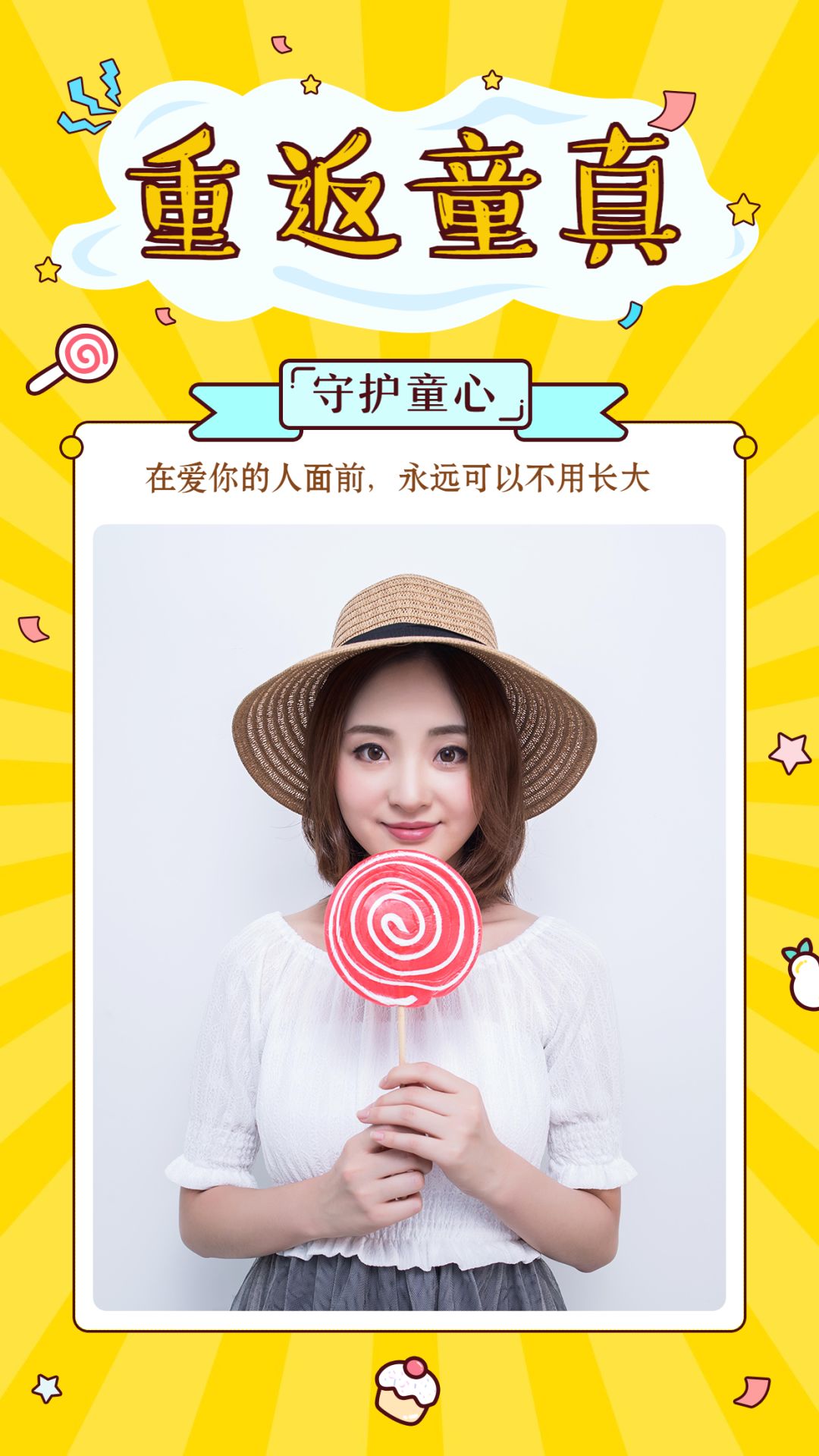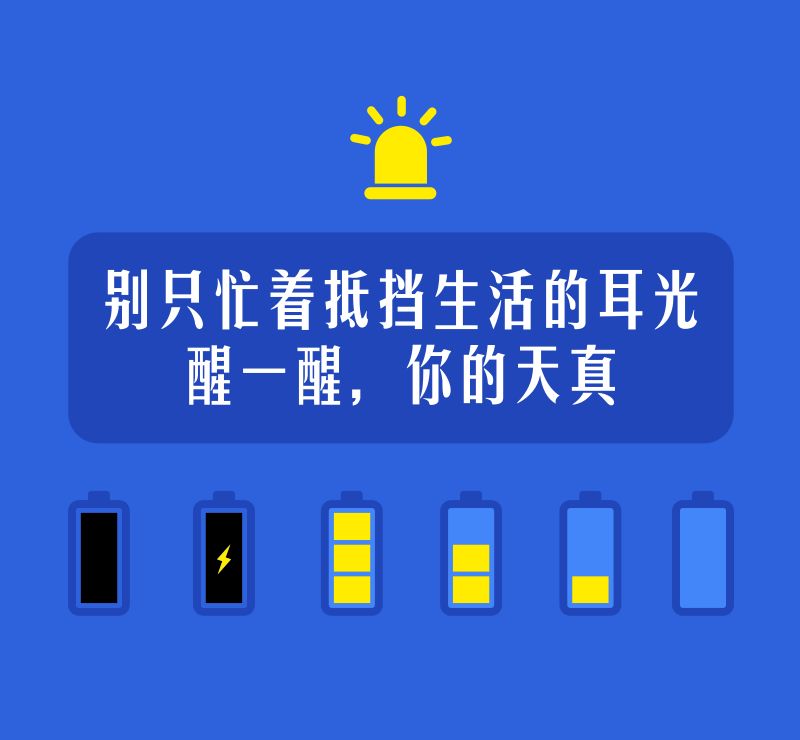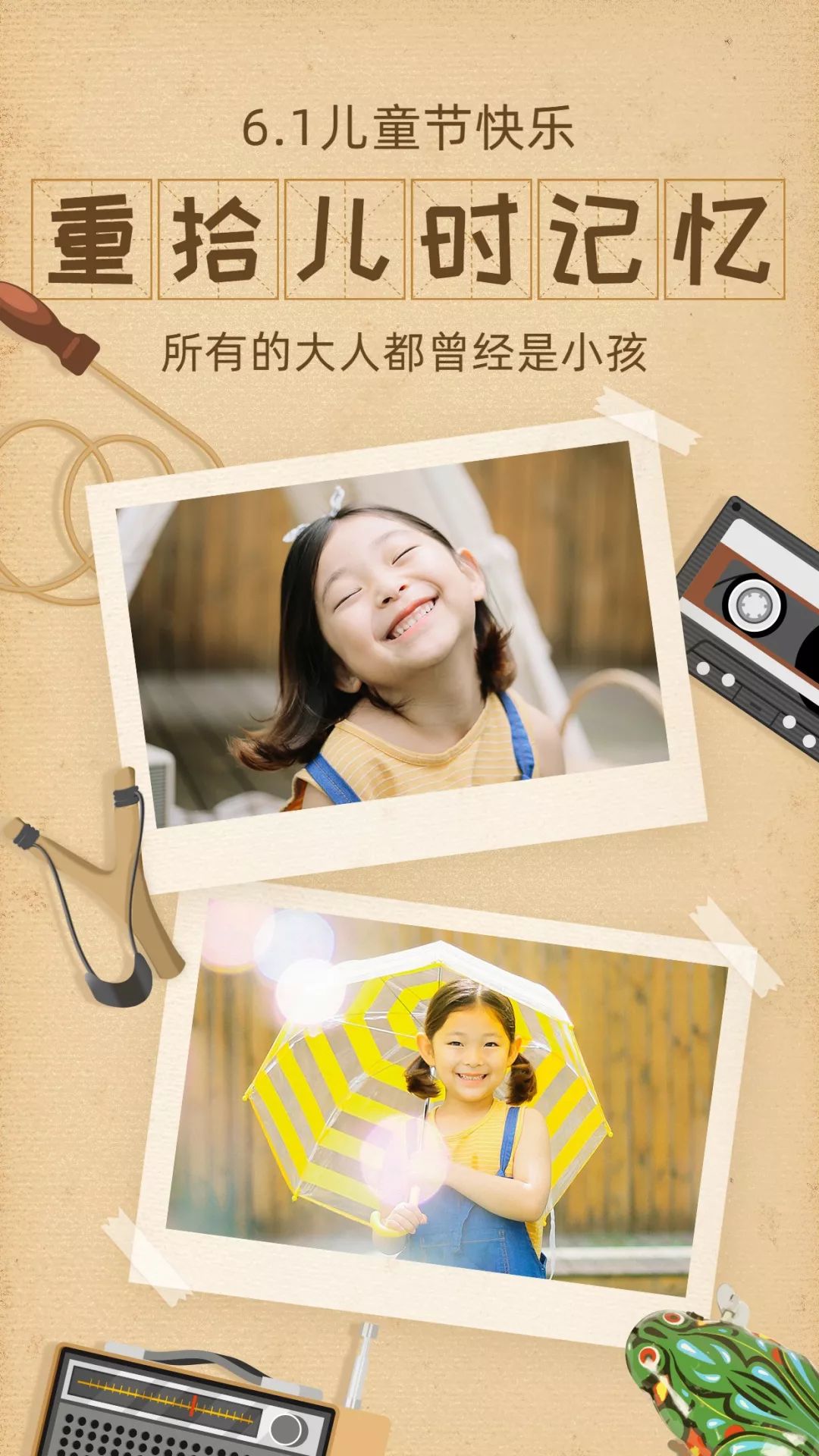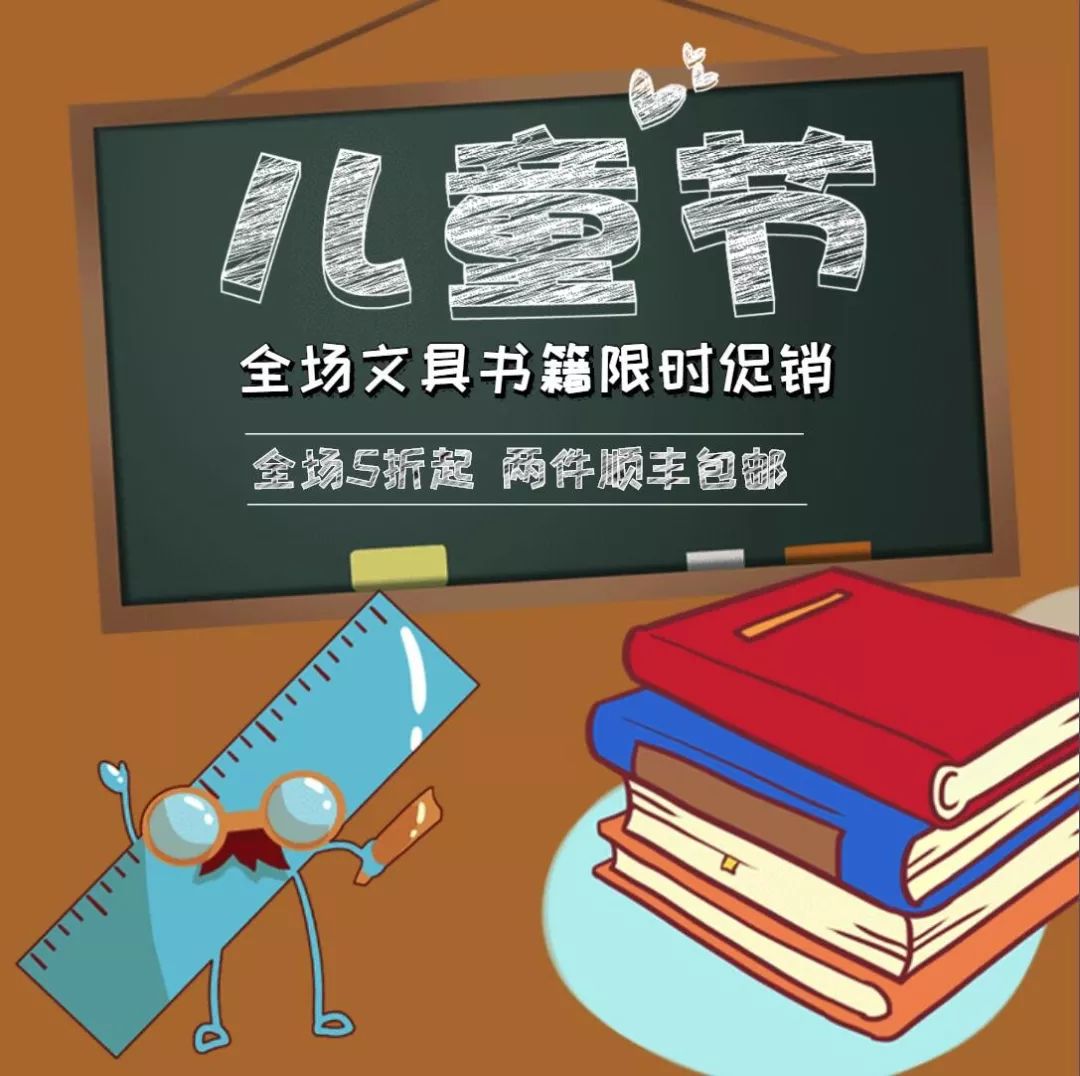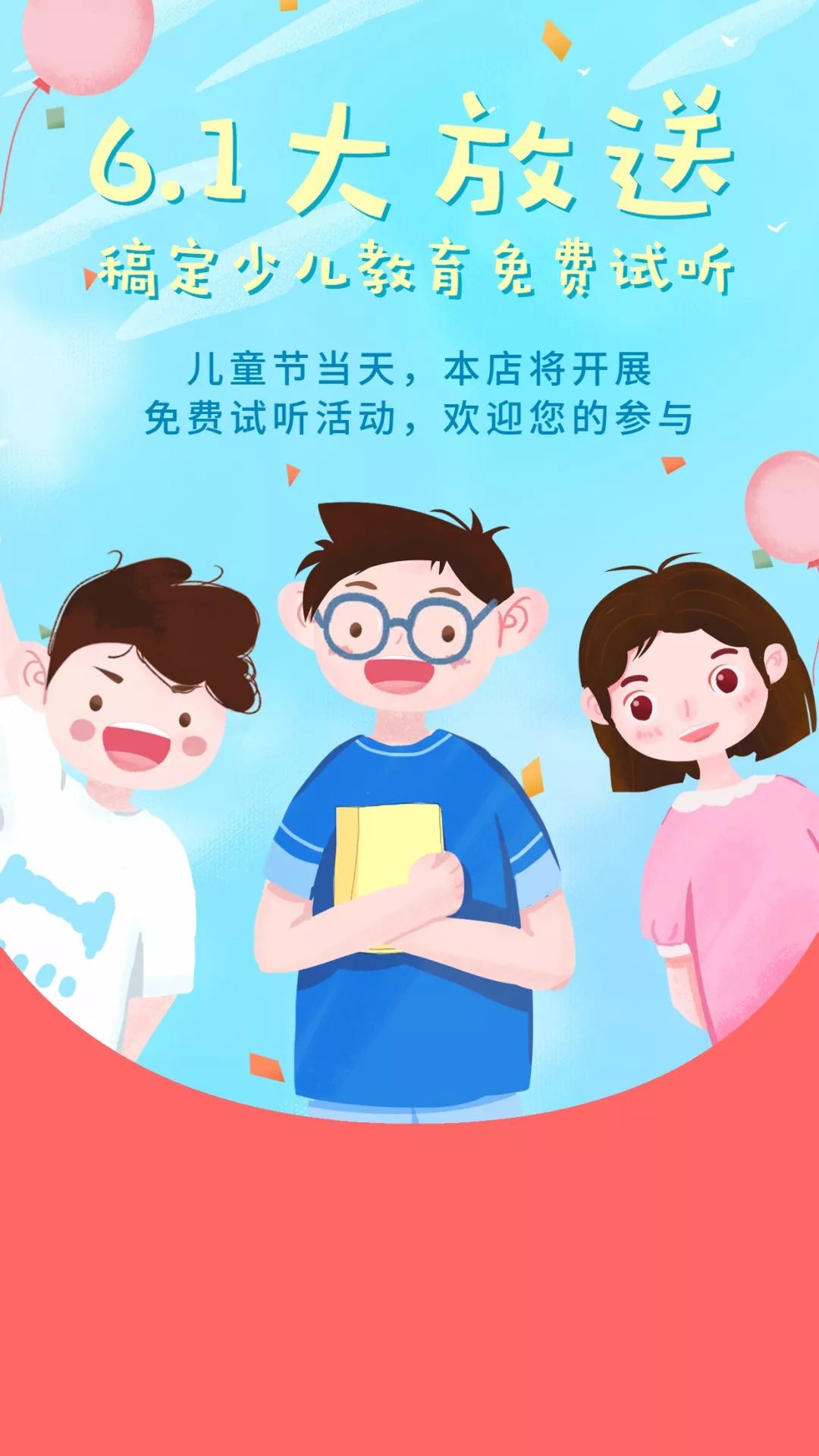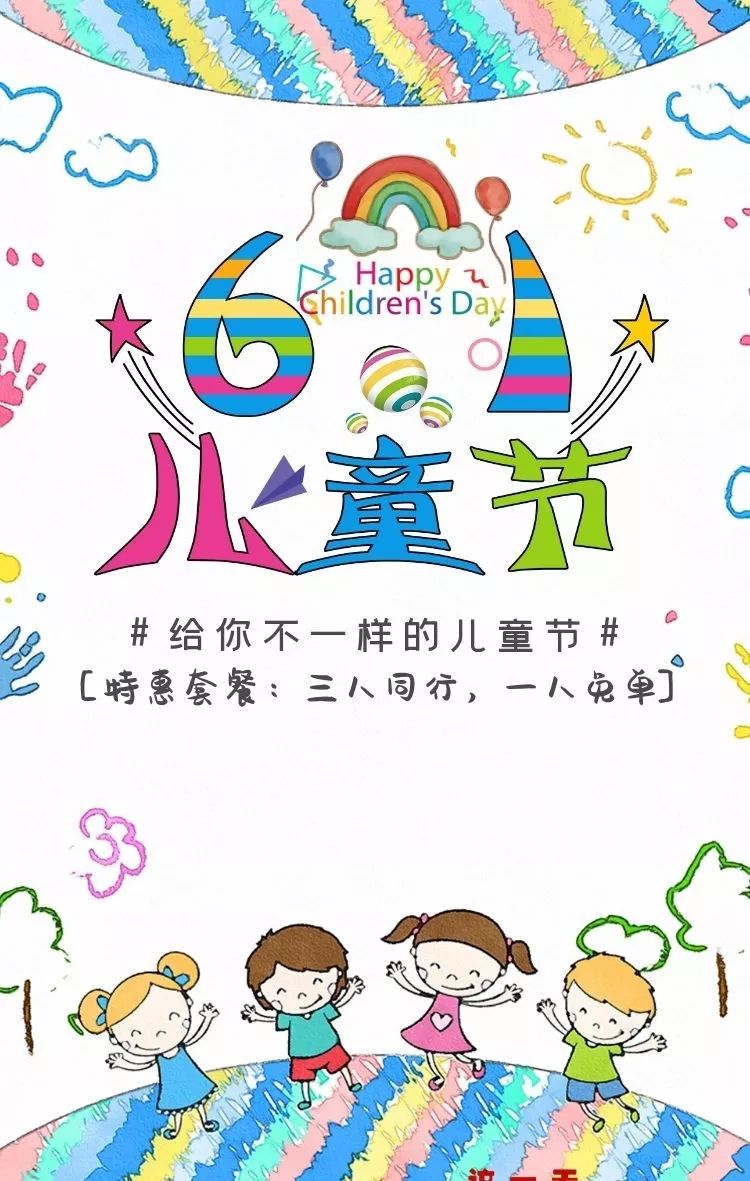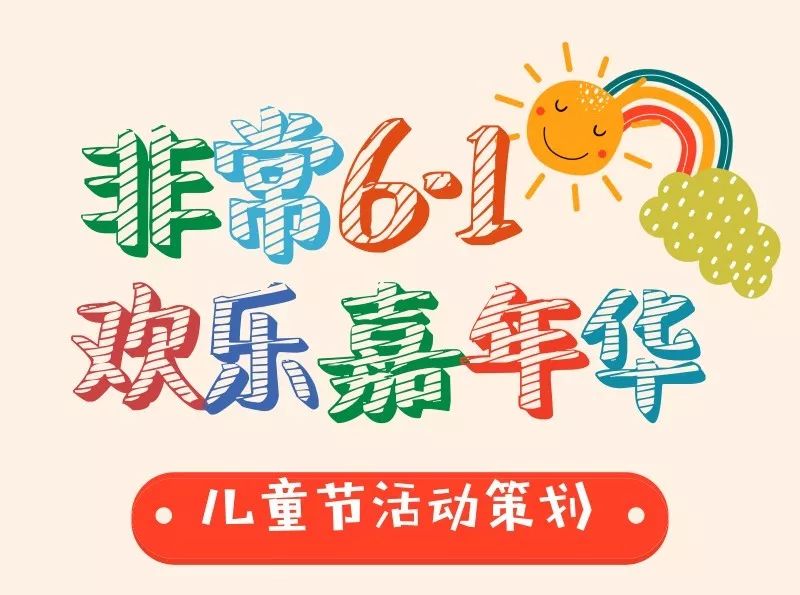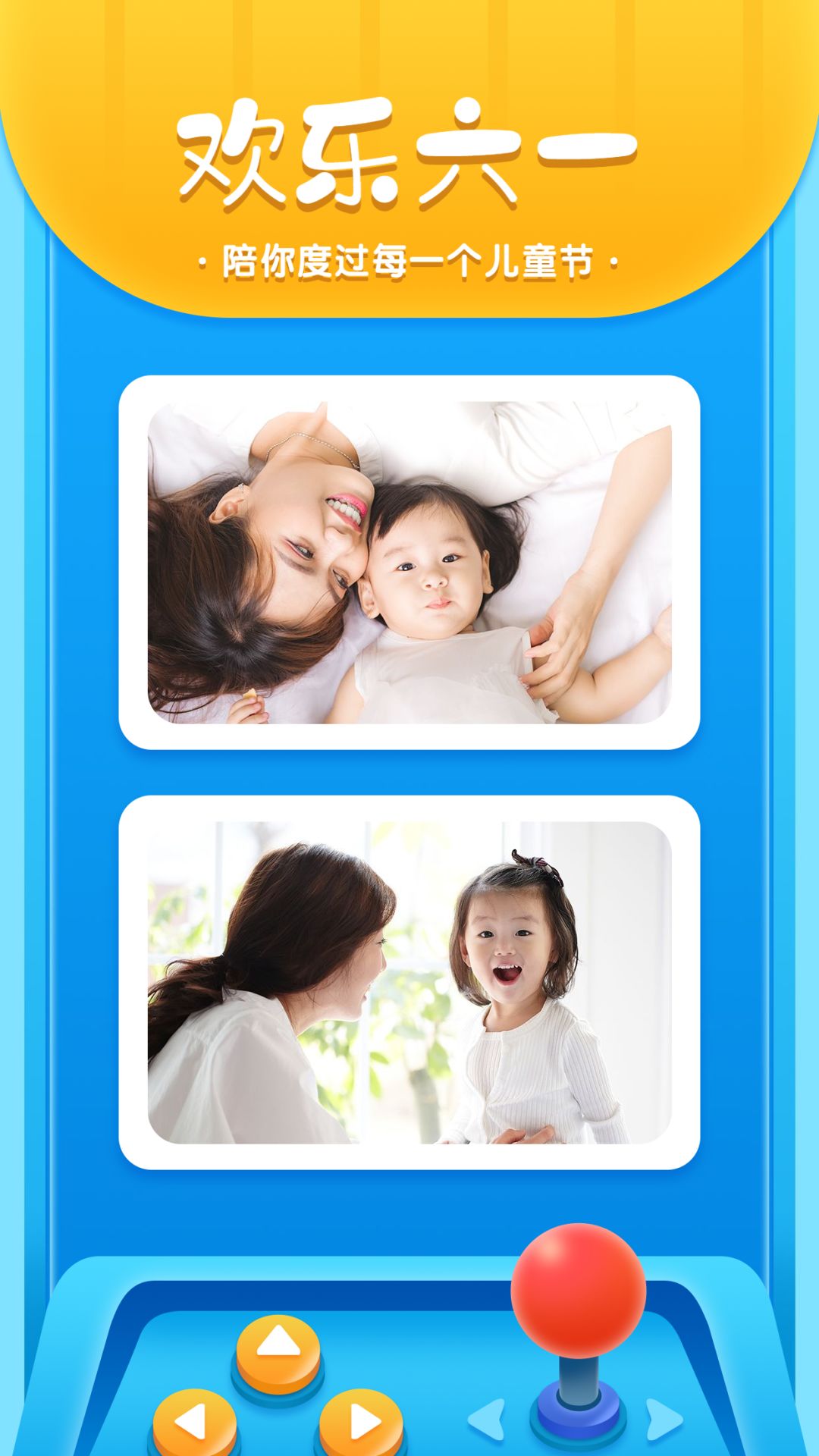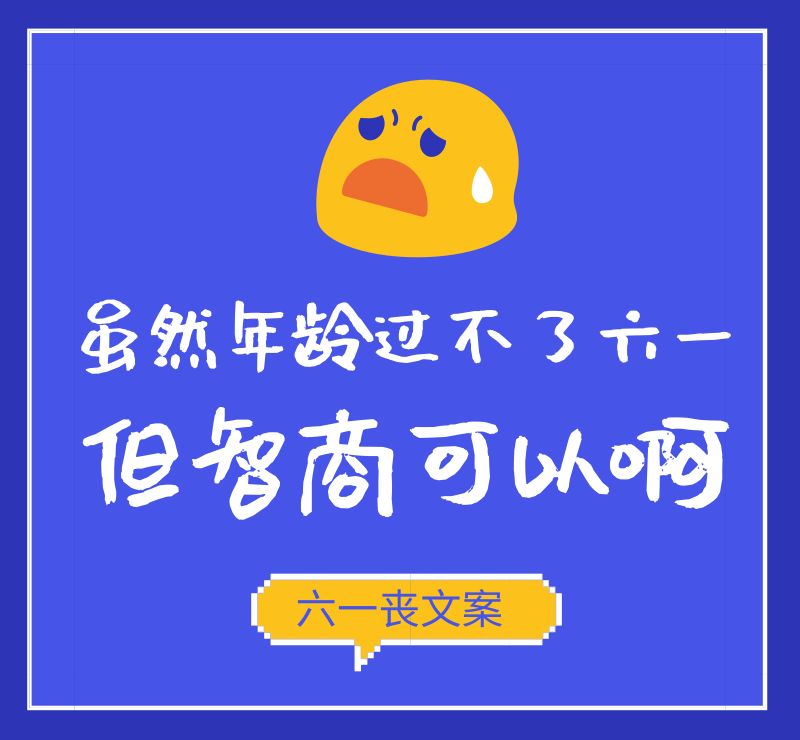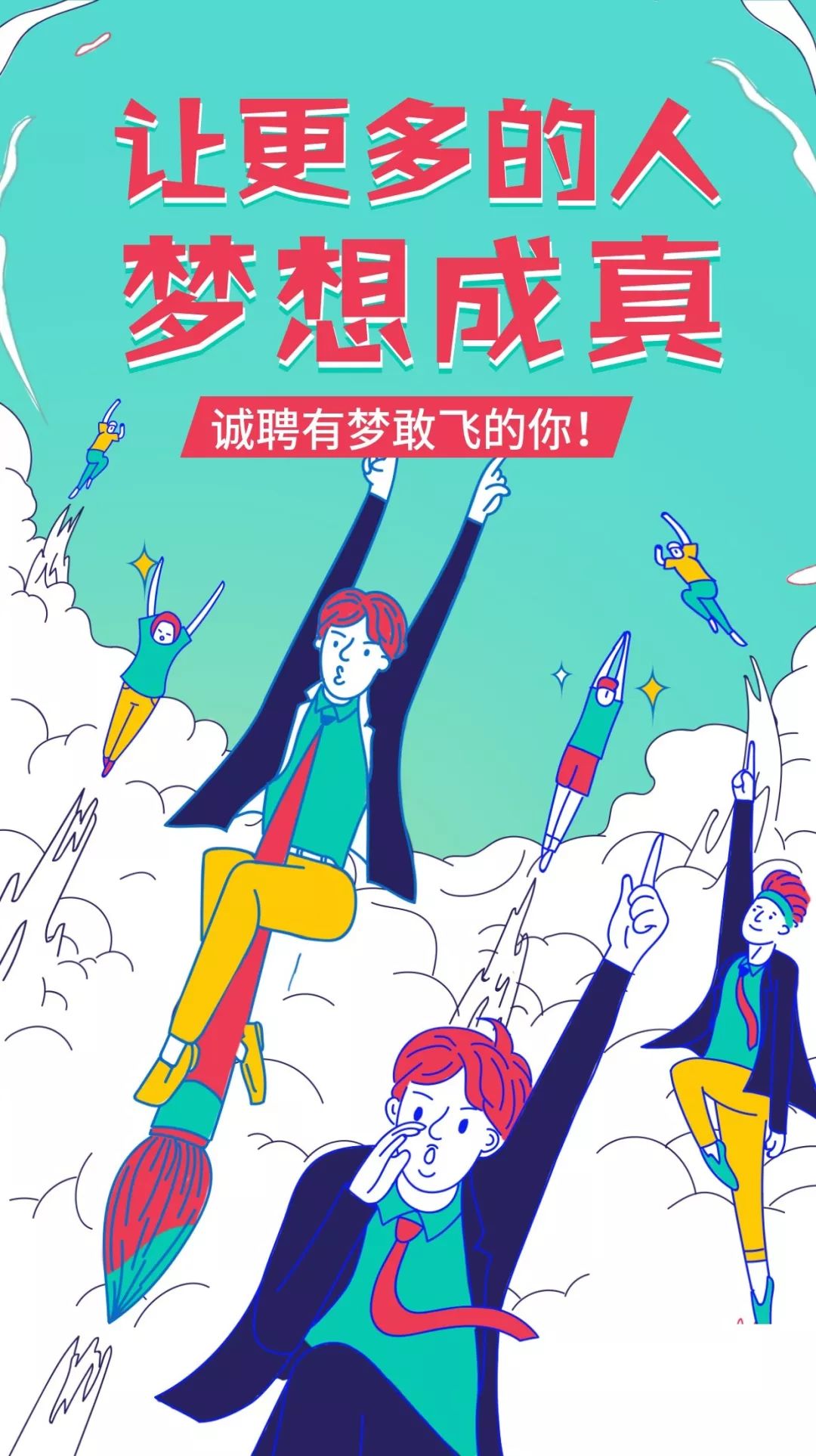
非常适合儿童节设计的字体分享
后天就是儿童节了,你的天真要不要放出来耍一耍?
毕竟成年人的世界太辛苦,还是偶尔放飞一下自我吧,哈哈!
▲汉仪长美黑
就像今天这些字体,保证你看第一眼,就想回到小时候~
▲汉仪小麦体
▲站酷快乐体
▲站酷庆科黄油体
▲汉仪字研卡通
▲华康海报体
▲Aa方萌
▲沐瑶软笔手写体
▲汉仪彩蝶体
▲汉仪跳跳体
▲汉仪新蒂黑板报
▲汉仪糯米团
▲汉仪铸字童年体
▲汉仪趣黑
▲汉仪铸字木头人
▲汉仪星球体